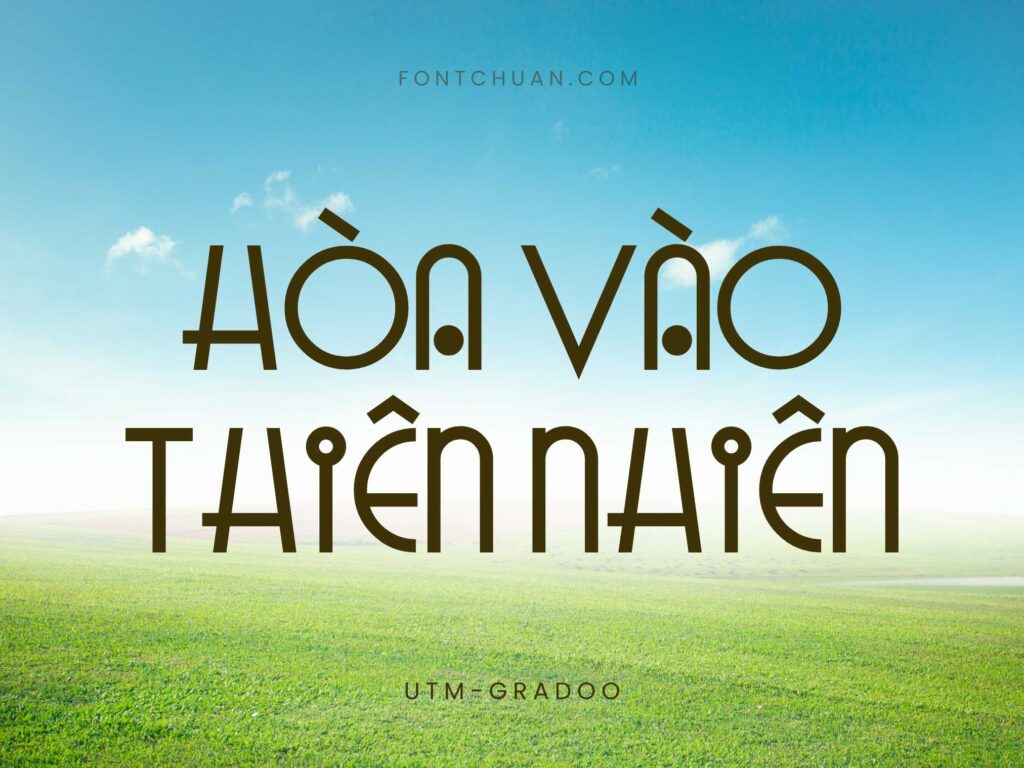
Font UTM Gradoo Việt Hóa
Gradoo là một font chữ độc đáo được thiết kế bởi Nick’s Fonts, lấy cảm hứng từ một poster du lịch Ý những năm 1930. Font này kết hợp sự thanh lịch cổ điển với những nét hiện đại, đồng thời mang một phần phong cách Font cổ trang, tạo nên sự hấp dẫn đặc biệt và cảm giác hoài cổ cho người nhìn. Hiện tại, thông tin về nhà phát hành và năm phát hành cụ thể chưa được công bố rộng rãi. Font Gradoo đã được Việt hóa để hỗ trợ tiếng Việt bởi Thiên Minh, ngoài ra còn hỗ trợ hơn 200 ngôn ngữ khác, giúp mở rộng khả năng ứng dụng trong thiết kế đa dạng. Font này được thành viên của Font Chuẩn sưu tầm và chia sẻ nhằm đáp ứng nhu cầu bạn đọc, cung cấp nguồn tham khảo chất lượng và ứng dụng thực tế vào các dự án thiết kế.
Về đặc điểm thiết kế, Gradoo sở hữu cấu trúc chữ với các đường cong mềm mại, độ tương phản vừa phải và độ dày trung bình, tạo cảm giác thanh lịch và dễ đọc. Font này không có ligatures đặc biệt, nhưng sự đơn giản trong thiết kế giúp nó linh hoạt trong nhiều ứng dụng. Gradoo phù hợp cho các thiết kế quảng cáo, biển hiệu, thiệp mời và các dự án nghệ thuật. Các ngành nghề như thời trang, mỹ thuật, quảng cáo và truyền thông có thể tận dụng font này để tạo nên sự khác biệt và thu hút trong các ấn phẩm của mình.